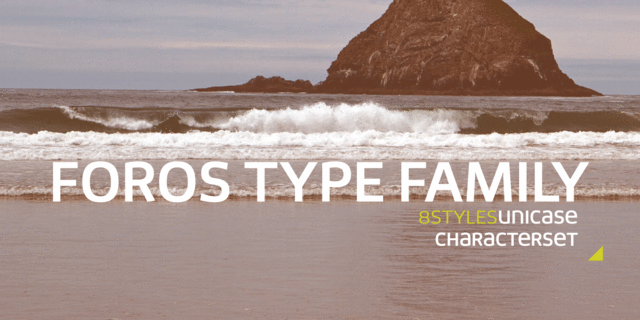
Шрифт Foros™ (Форос™) относится к классу современных гуманистических гротесков. Гарнитура состоит из 8 начертаний четырех насыщенностей, каждое из которых расширено комплектом знаков «юникейз» (своеобразной смесью строчных и прописных форм, спроектированных для совместного применения в одном размере), оформленным в отдельные стилистические сеты. Шрифт разрабатывает тему соединения грубоватых геометрических и открытых гуманистических форм, демонстрируя одновременно и упрямство, и деликатность. Слегка заквадраченные формы овалов придают рисунку Фороса основательность и устойчивость, а косые срезы окончаний диагональных штрихов К и R и скругления в местах присоединений полуовалов к основным штрихам (B,D,P,R) добавляют эмоциональности. Эти особенности формы создают образ, обеспечивающий широкий спектр применения гарнитуры в акцидентном наборе. Гарнитура спроектирована дизайнером Олегом Карпинским. Выпущена компанией ПараТайп в 2013 году.